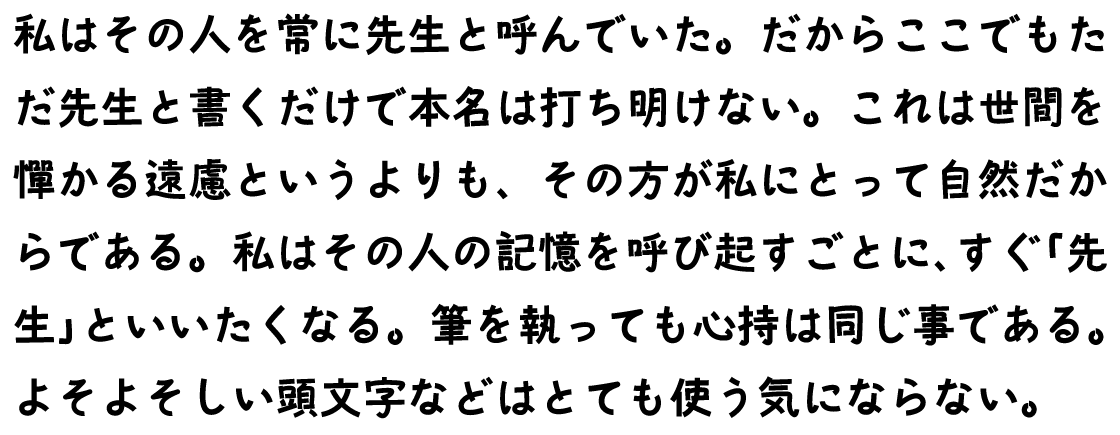
モトヤ角ノート
書体解説
モトヤ角ノートは、モトヤノートの骨格を利用したバリエーション書体の一つです。モトヤノートが持っている柔らかさや優しさに対して、モトヤ角ノートでは始筆と終筆に角ができることによって生じる輪郭同士の隙間を活かして、子供のような無邪気さや、元気でハキハキとした明るい表情を持たせています。